La typographie est un art millénaire qui permet de communiquer...
Guide Pratique sur la Typographie pour les Étudiants en STD2A
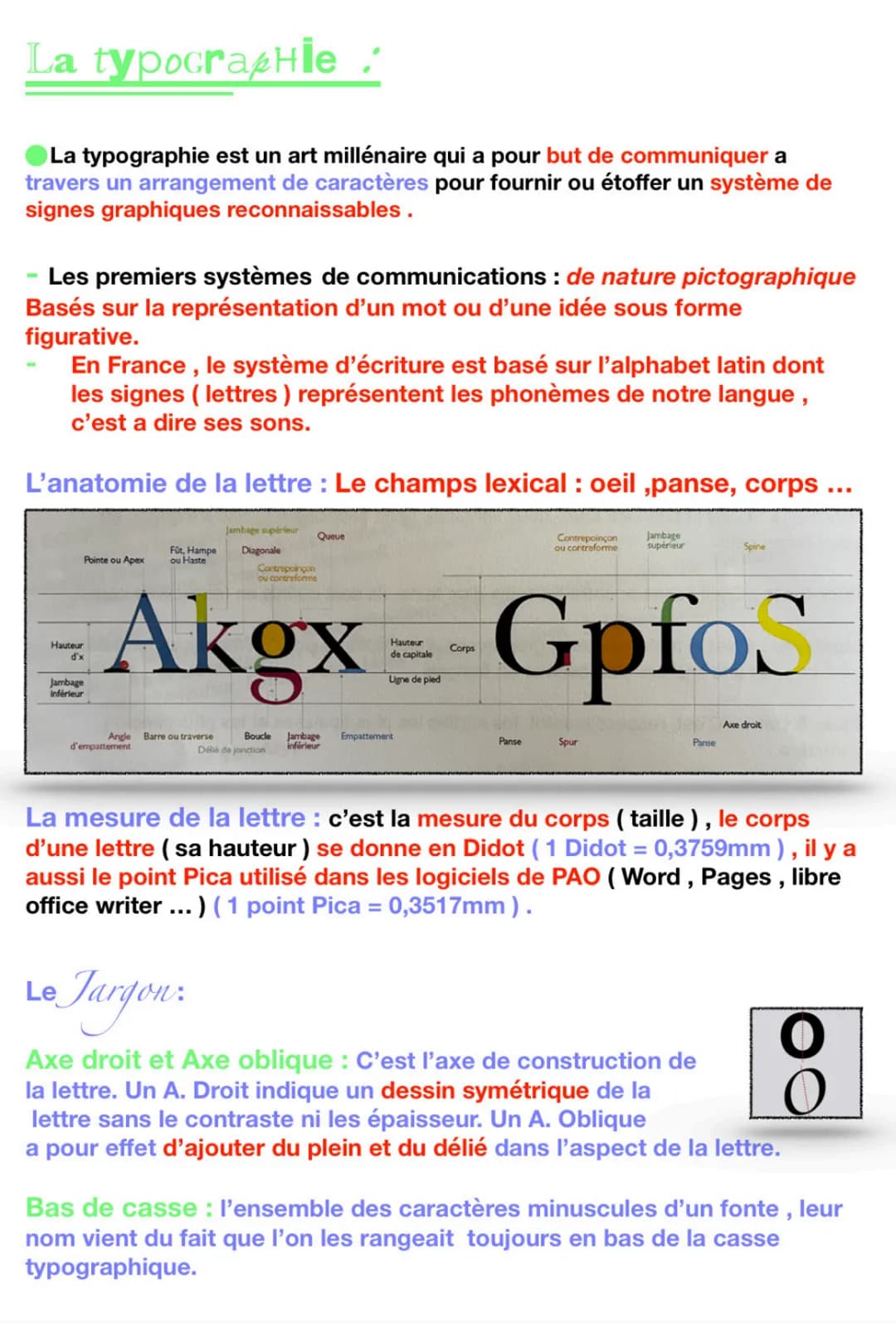
L'anatomie de la lettre
La typographie a évolué depuis les premiers systèmes de communication pictographiques, basés sur la représentation figurative des idées. En France, notre système d'écriture repose sur l'alphabet latin, dont les signes représentent les phonèmes (sons) de notre langue.
L'anatomie d'une lettre comporte plusieurs éléments essentiels à connaître. Parmi eux, on retrouve l'œil (partie visible du caractère), la panse (partie arrondie fermée), le corps (taille du caractère) et la queue (trait descendant).
D'autres éléments structurent les lettres comme la pointe (ou apex), la hampe (ou haste, trait vertical montant), les jambages (traits verticaux inférieurs ou supérieurs), et la diagonale (trait oblique). Le contrepoinçon (ou contreforme) désigne l'espace vide à l'intérieur d'une lettre.
💡 Astuce : Pour mieux mémoriser l'anatomie des lettres, observe-les comme des personnes avec un corps, des jambes (jambages) et même une queue pour certaines !
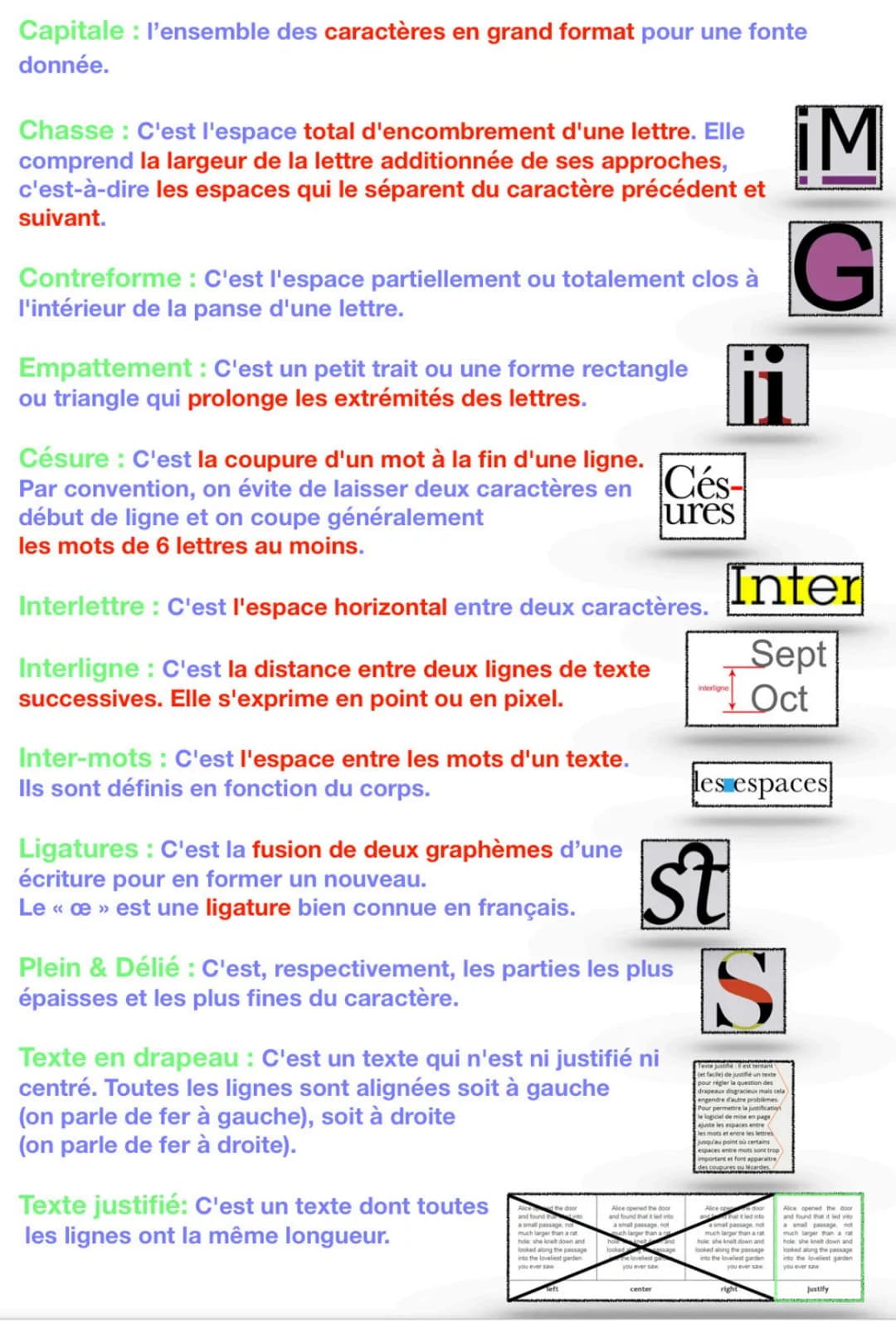
Le vocabulaire technique de la typographie
La capitale désigne l'ensemble des caractères en grand format pour une fonte donnée, tandis que la chasse représente l'espace total qu'occupe une lettre, y compris les espaces qui la séparent des caractères adjacents.
Les empattements sont ces petits traits qui prolongent les extrémités des lettres, ajoutant du caractère à la typographie. Quant à la césure, elle correspond à la coupure d'un mot en fin de ligne, avec pour règle d'éviter de laisser deux caractères seulement au début d'une ligne.
L'espacement est crucial en typographie : l'interlettre (espace entre deux caractères), l'interligne (distance entre deux lignes de texte) et l'inter-mots (espace entre les mots) contribuent tous à la lisibilité d'un texte. Les ligatures comme le "œ" français représentent la fusion de deux lettres pour en former une nouvelle.
🔍 À retenir : Un texte peut être présenté de différentes façons : en drapeau (aligné à gauche ou à droite) ou justifié (toutes les lignes ont la même longueur), chaque style ayant son propre impact visuel.